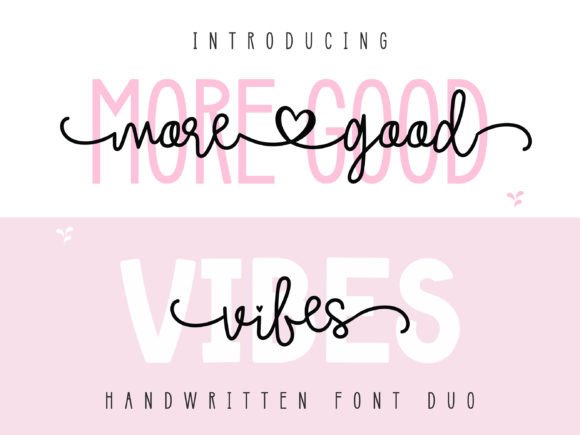
More Good Vibes Duo
找到合适的设计元素可能具有挑战性,但 More Good Vibes Duo 提供了一系列出色的藏品,可瞬间提升您的作品质量。
精心制作的 More Good Vibes Duo 提供干净的矢量、流畅的排版以及让您安心的商业许可证。
无论您是创建 POD(按需打印)产品、婚礼邀请函还是社交媒体图形,More Good Vibes Duo 都是理想的选择。